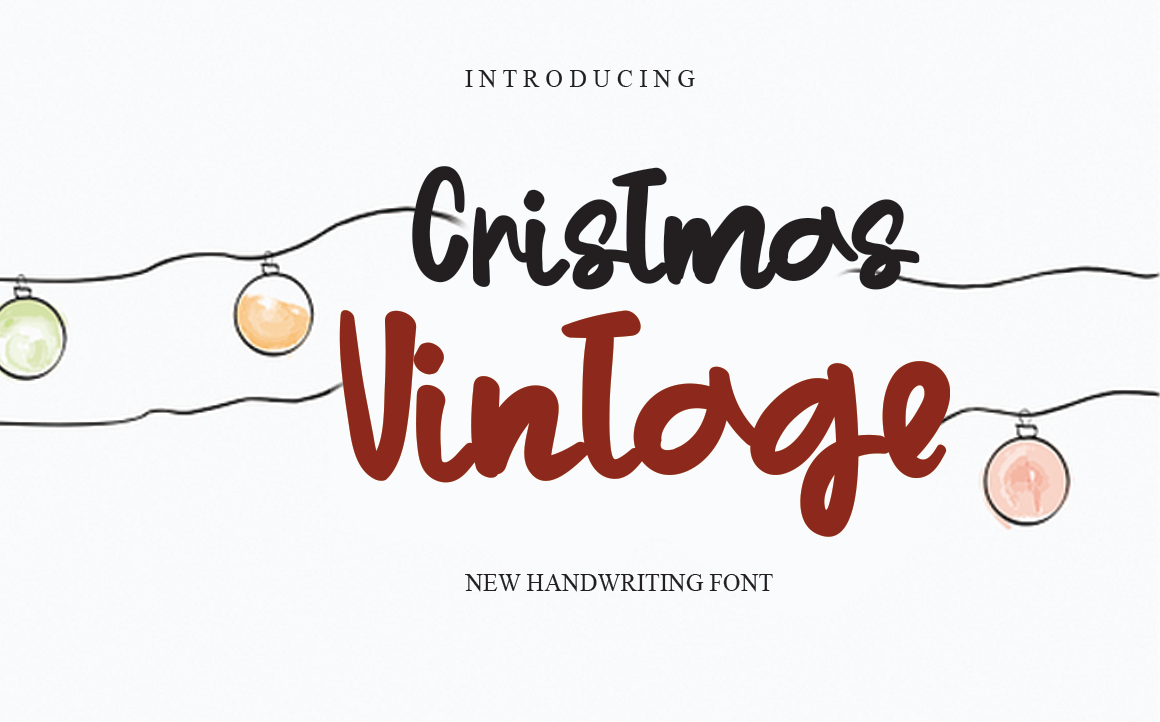
Christmas Vintage Font – Download Grátis
Esta fonte ‘Christmas Vintage Font’ é uma criação única e divertida que captura a essência do Natal com suas letras manuscritas. Confeccionada pelo designer Levincreative, ela combina um estilo vintage moderno para tornar sua escrita ainda mais especial e autêntica. Seja você um amante da internet que busca uma fonte ideal para o Instagram ou um apreciador de arte livre criando projetos DIY, esta font pode transformar qualquer ideia artística em um verdadeiro trabalho de arte. Composta por linhas frouxas e traços delicados, ela transmite um ar vintage enquanto continua a ser adaptável aos diferentes estilos e usos que você possa imaginar. Experimente inseri-la em cartões de Natal, calendários ou até mesmo em presentes personalizados para dar um toque único à sua produção artística natalina.